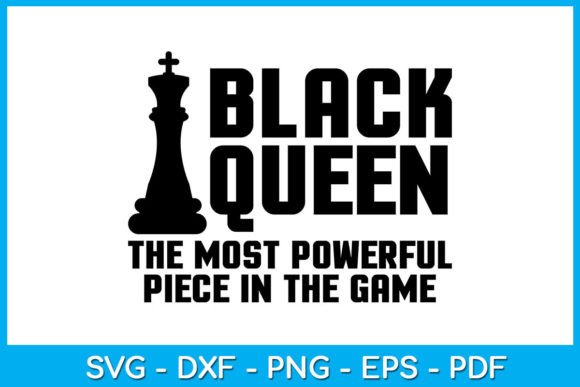
Black Queen the Most Powerful Piece in T
Пошук відповідних елементів дизайну може бути складним, але Black Queen the Most Powerful Piece in T пропонує виняткову колекцію, яка миттєво покращить вашу роботу.
Створений з високою точністю, Black Queen the Most Powerful Piece in T забезпечує чисті вектори, плавну типографіку та комерційну ліцензію для вашого спокою.
Незалежно від того, чи створюєте ви продукти POD (друк на вимогу), весільні запрошення або графіку для соціальних мереж, Black Queen the Most Powerful Piece in T стане ідеальним вибором.